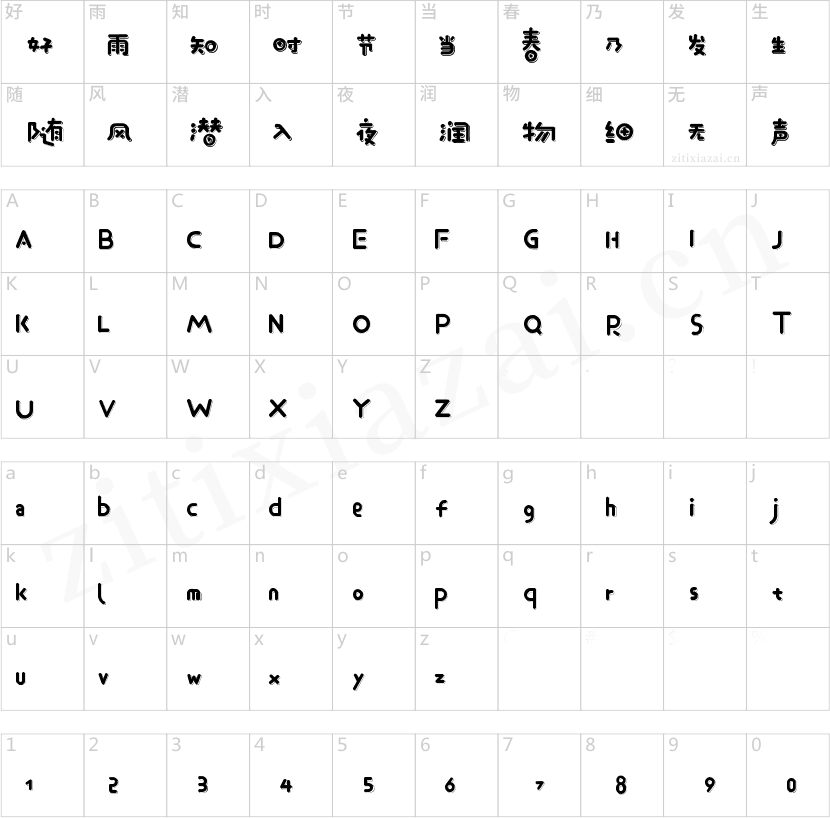
字魂214号-童话故事体
字魂字体字小魂童话故事体字体是由字魂创意字库设计并生产的一款可商用的字体,被收录于字小魂系列。该字体支持GB-2312标准,包含6763个中文、字母、符号和数字,字体类型偏向创意字体,具有活泼、动漫、可爱、简约、时尚、圆润的风格,在市面上广泛用于广告电商、排版阅读、游戏动漫等场景。